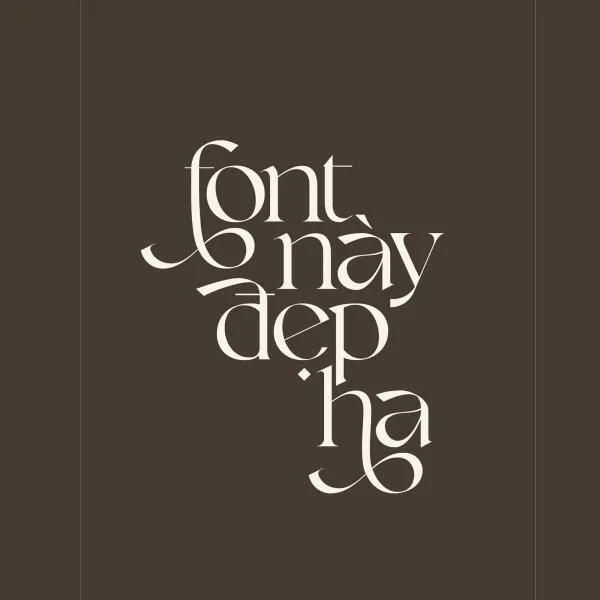
Tổng quan về Font Black
Đây là một font mình đã sưu tầm để làm dự án và thấy khá ấn tượng nên đã Việt hóa, phông chữ mang phong cách cổ điển và hiện đại hoàn hảo cho nhiều dự án như thiết kế logo, thiệp mời, sự kiện, quảng cáo, thiết kế sản phẩm, văn phòng phẩm, nhãn mác và nhiều thiết kế khác nhau.
Chi tiết ký tự của Font Black
Font đã được Việt hóa đầy, kerning, feature và tối ưu hóa lại để sử dụng trên hầu hết các phần mềm và ứng dụng.